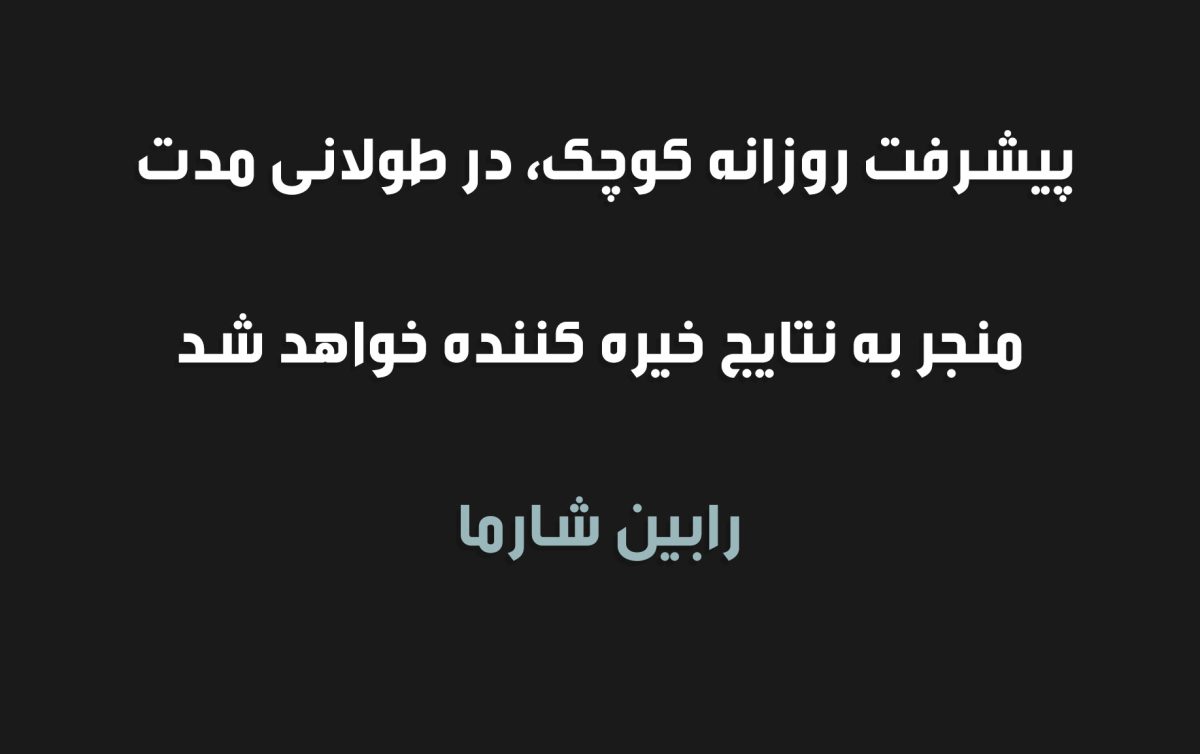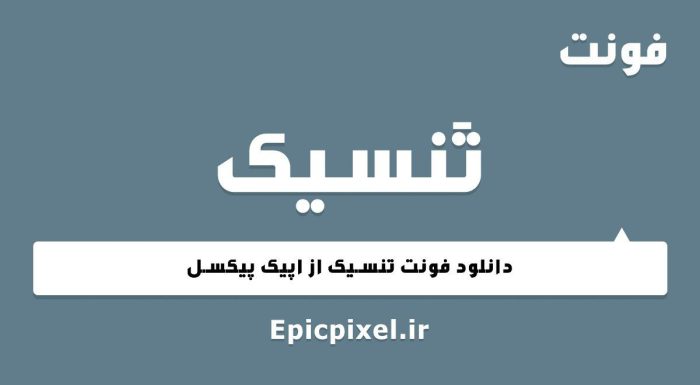
6 فونت تنسیک عربی فارسی Tanseek
در دنیای پویای طراحی، انتخاب فونت مناسب نقش بسزایی در انتقال پیام و جذابیت بصری ایفا می کند. فونت ها می توانند حال و هوا، سبک و حتی هدف یک طرح را مشخص کنند. فونت تنسیک (Tanseek)، یک قلم مدرن و حرفه ای است که با طراحی شکیل و ویژگی های کاربردی خود، توجه بسیاری از طراحان را به خود جلب کرده است. این مجموعه فونت در دو ورژن کلی با نام های مدرن (Modern) و بهیج (Bahij) ارائه می شود، و تمرکز ما در اینجا بر معرفی جزئیات نسخه تنسیک مدرن پرو عربیک (Tanseek Modern Pro Arabic) است که در منابعی مانند اپیک پیکسل معرفی شده است.
فونت تنسیق مدرن پرو: قلمی چهار وزنی و چندزبانه با حالتی گرافیکی برای طراحی های خلاقانه Tanseek Modern Pro
فونت تنسیک مدرن پرو عربیک یک فونت عربی است که با دقت و توجه، شامل طراحی حروف فارسی مانند گ، چ، پ، ژ نیز شده است. این ویژگی امکان استفاده آسان و بدون مشکل از این فونت را برای تایپ متون فارسی فراهم می کند. علاوه بر فارسی و عربی، تنسیک از زبان های انگلیسی و اردو نیز پشتیبانی می کند، که آن را به یک قلم چهار زبانه کاربردی برای طراحان در مناطق مختلف تبدیل کرده است.
از نظر ظاهری، طراح در این فونت نگاهی گرافیکی و فانتزی داشته است. این بدان معناست که تنسیک یک فونت رسمی نیست که برای نگارش پایان نامه یا نامه های اداری مناسب باشد. بلکه طراحی آن با هدف بخشیدن جذابیت و زیبایی دو چندان به طرح های گرافیکی صورت گرفته است. این رویکرد طراحی، آن را برای پروژه هایی که نیاز به حس خلاقیت و غیررسمی دارند، ایده آل می سازد. یکی از ویژگی های ظاهری آن، ارتفاع کم حروف است که به جذاب تر شدن فونت کمک شایانی کرده و به آن ظاهری فشرده و دلنشین می دهد.
دانلودمجموعه فونت تنسیک مدرن پرو شامل چهار ضخامت مختلف قلم است که گستره ای از حالات بصری را پوشش می دهد: بسیار ضخیم، ضخیم، معمولی و باریک. این تنوع وزنی، انعطاف پذیری لازم برای استفاده در بخش های مختلف یک طراحی را فراهم می کند؛ از تیترهای اصلی گرفته تا متون فرعی یا توضیحات کوچک. در تمام حروف در هر نسخه ای از این فونت، ضخامت قلم ثابت است و در مجموع پس از نوشتن یک کلمه یا یک جمله، یک ساختار یک دست و یکنواخت حاصل می گردد. این یکنواختی به ظاهر حرفه ای و شکیل فونت کمک می کند.
این فونت همچنین دارای طراحی های جایگزین برای برخی کاراکترها است که ظاهر آن ممکن است بسته به حروف انتخاب شده متفاوت باشد. این ویژگی امکان تنوع بیشتر در تایپوگرافی های نمایشی را فراهم می کند و دست طراح را برای خلق ترکیب های بصری خاص تر باز می گذارد.
با توجه به طراحی گرافیکی و فانتزی و نیز تنوع وزنی، فونت تنسیک مدرن پرو برای طیف گسترده ای از کاربردهای طراحی ایده آل است. می توان از آن برای طراحی انواع پوستر، لوگو و سایر المان های بصری که نیاز به جلوه ای مدرن و جذاب دارند، استفاده کرد. این فونت به خوبی برای طراحی انواع بنر و پوستر مذهبی و اسلامی نیز کاربرد دارد، جایی که طراحی خاص و زیبای آن می تواند به انتقال حس معنویت و زیبایی کمک کند. طراحی خاص و زیبای این فونت باعث می شود طراحان علاقه زیادی به استفاده از آن نشان دهند و برای جذاب کردن طرح های خود به آن روی بیاورند. این فونت یک ابزار قوی برای خلق طراحی های چشمگیر در چهار زبان مختلف است.
در نهایت، فونت تنسیک مدرن پرو یک مجموعه چهار وزنی زیبا و کاربردی برای طراحی های گرافیکی فارسی، عربی، انگلیسی و اردو است که با وجود محدودیت استفاده تجاری، فرصتی عالی برای پروژه های شخصی و آموزشی فراهم می کند و به لطف سازگاری با تمامی پلتفرم ها، به راحتی در دسترس طراحان قرار دارد تا به طرح های خود جلوه ای مدرن و گرافیکی ببخشند.